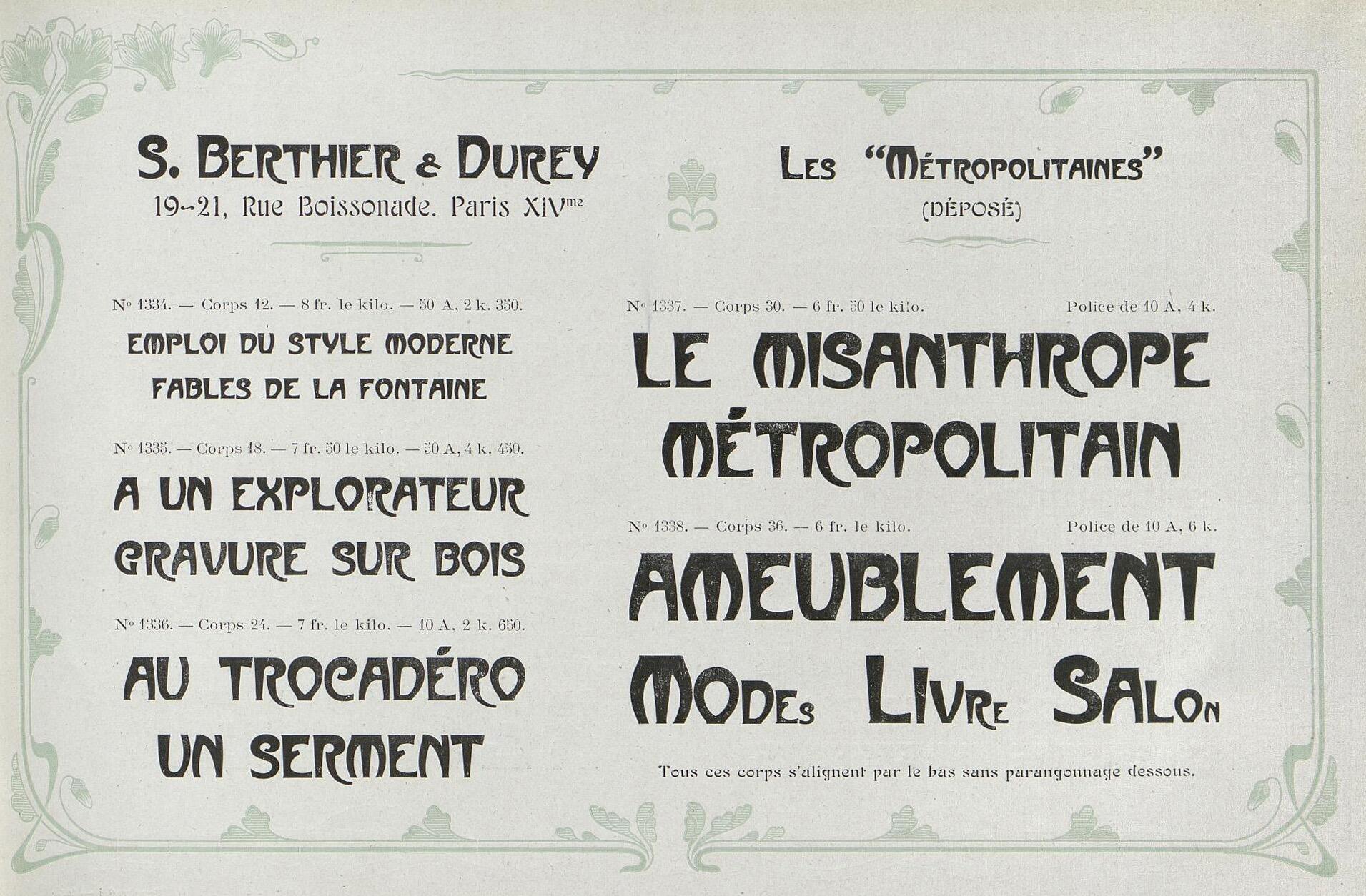
Font-Wiki: Metropolitaines
• 1905
• Antiqua dekorativ
Hector Guimard (1867–1942) war ein französischer Architekt, der zur Zeit des Jugendstils wirkte. In Paris schuf er Anfang des 20. Jahrhunderts die Stationseingänge der Metro. Dazu gehörte auch ein charakteristischer Jugendstil-Schriftzug, der später auch als Druckschrift herausgebracht wurde. Digitalisierungen gibt es heute zum Beispiel von URW++, Linotype und Elsner+Flake.